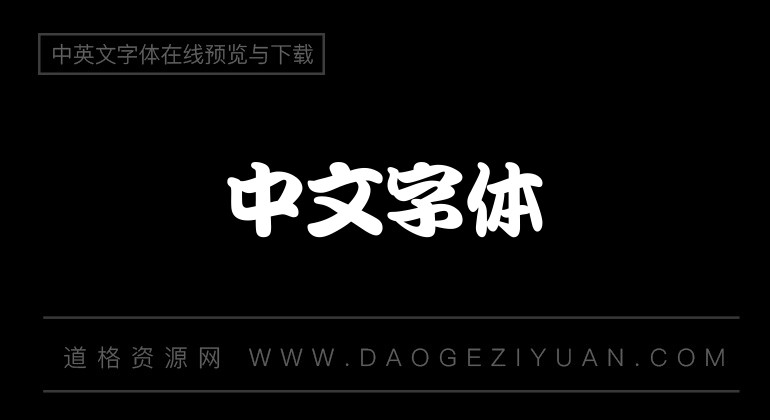
鯱旗勘亭流W7
? 鯱旗勘亭流W7字体是一款中文字体,它是由台湾字体设计师林晨铭创作的,并以台湾鯱旗勘亭流派的書法风格为原型而设计。该字体以書法的精神为主,笔画粗细和笔画结构都比较复杂,更加符合書法的精神。它的字体结构比较复杂,比较自然,更有艺术性,可以更好地表达出書法的精神和美感。
鯱旗勘亭流W7是一款非常不错的手写艺术字体,具有很好的视觉感,适合于文化类的宣传设计、商业类品牌的广告和产品包装设计以及个性化文字排版等较多场景。